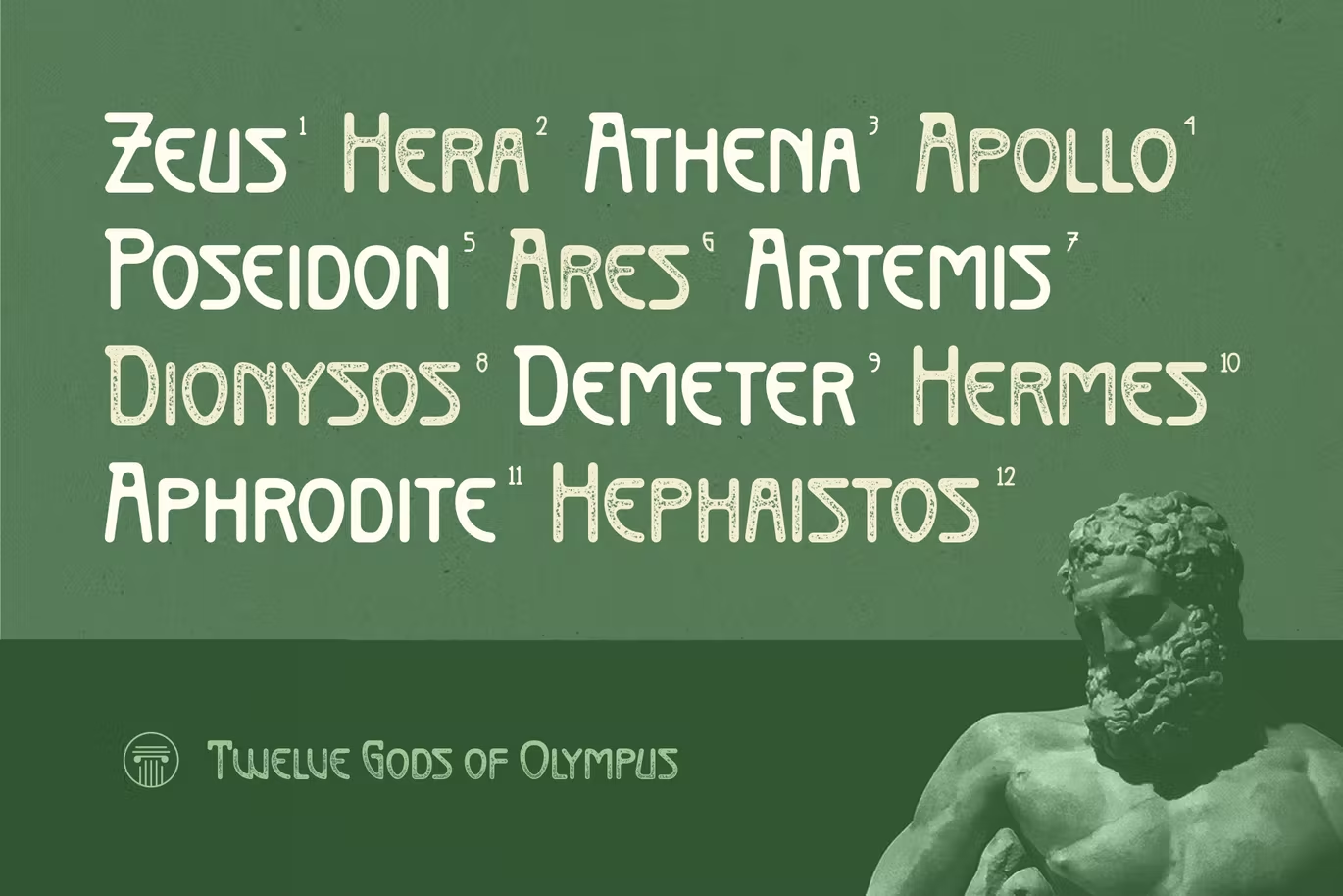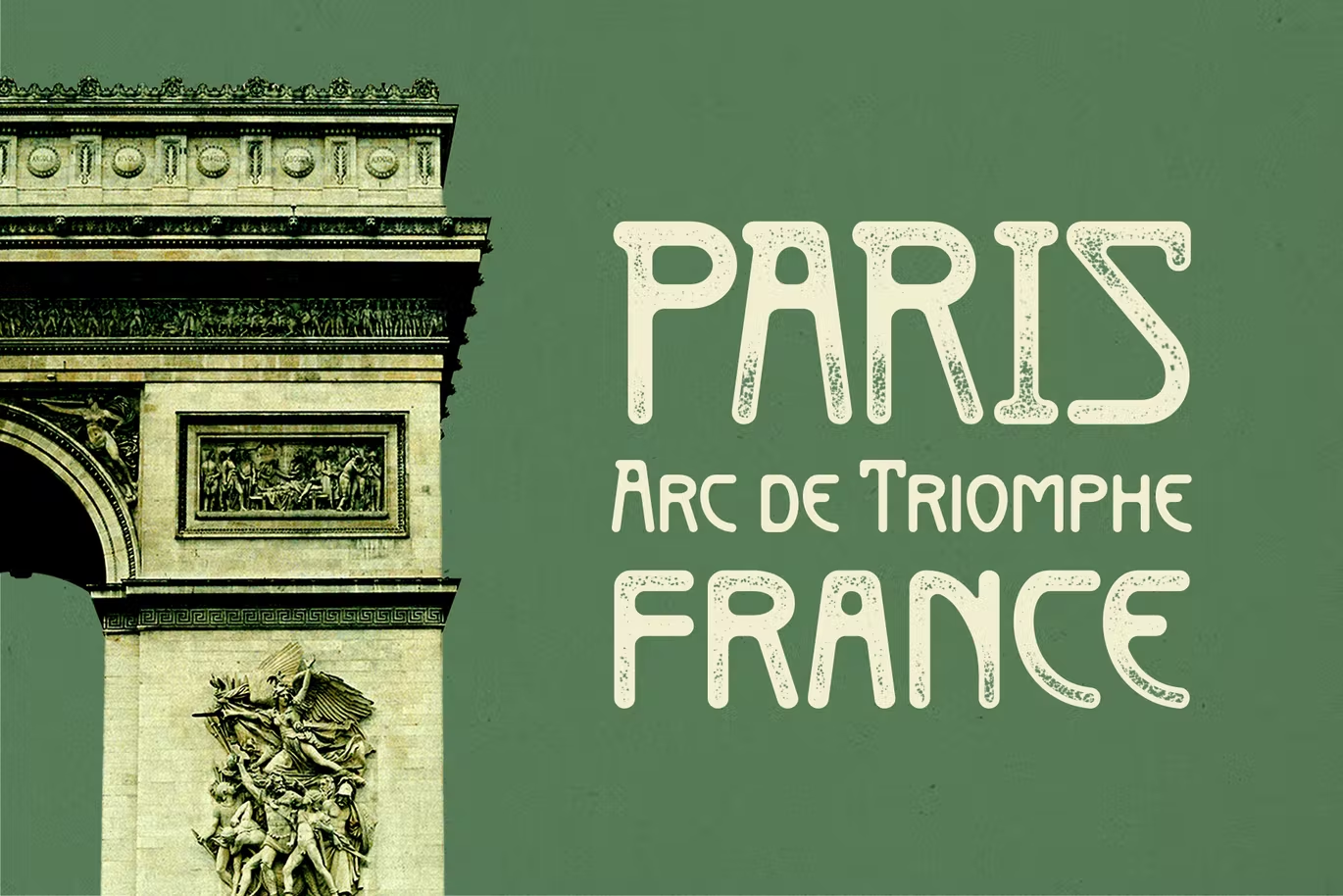
Arestapolus Font
Description de Arestapolus Font
ARESTAPOLUS est une police vintage avec un style légèrement moderne, une police qui est principalement une police sans empattement avec des coins arrondis. Parce qu’il a une touche moderne, en plus de convenir aux designs vintage, il peut également être utilisé pour des designs modernes ou des textes pas trop longs.
Cette police est une police entièrement en majuscules avec une minuscule légèrement inférieure à la majuscule. Cette police unique est idéale pour les designs simples et nuancés ou peut également être utilisée pour soutenir des designs artistiques.